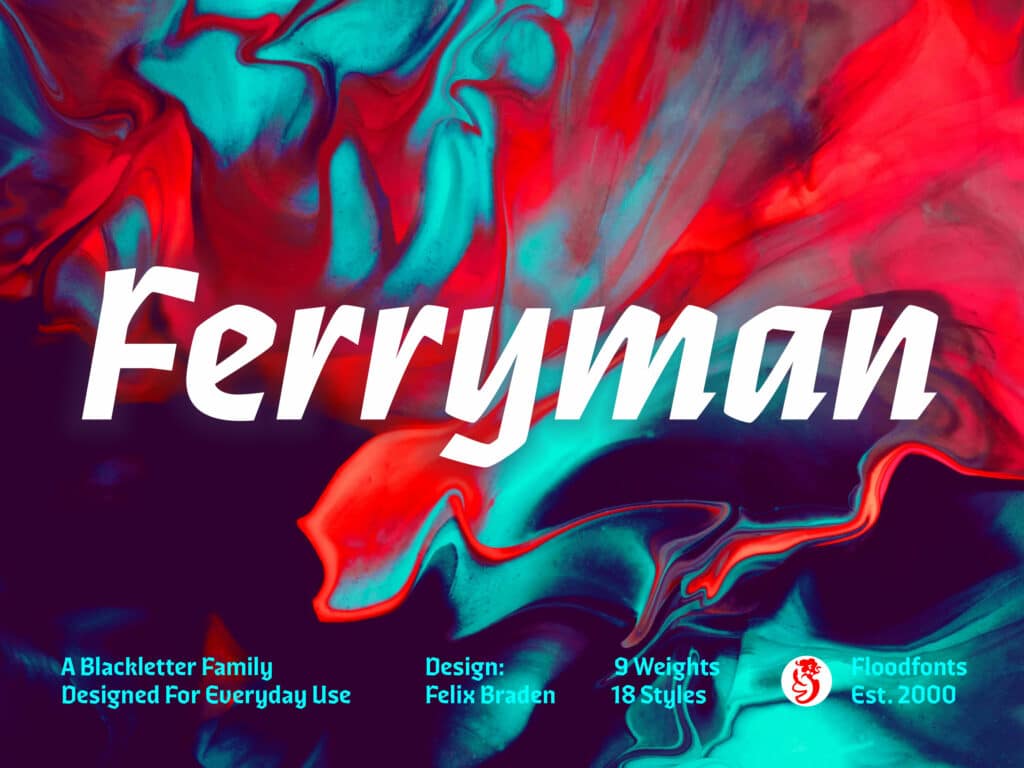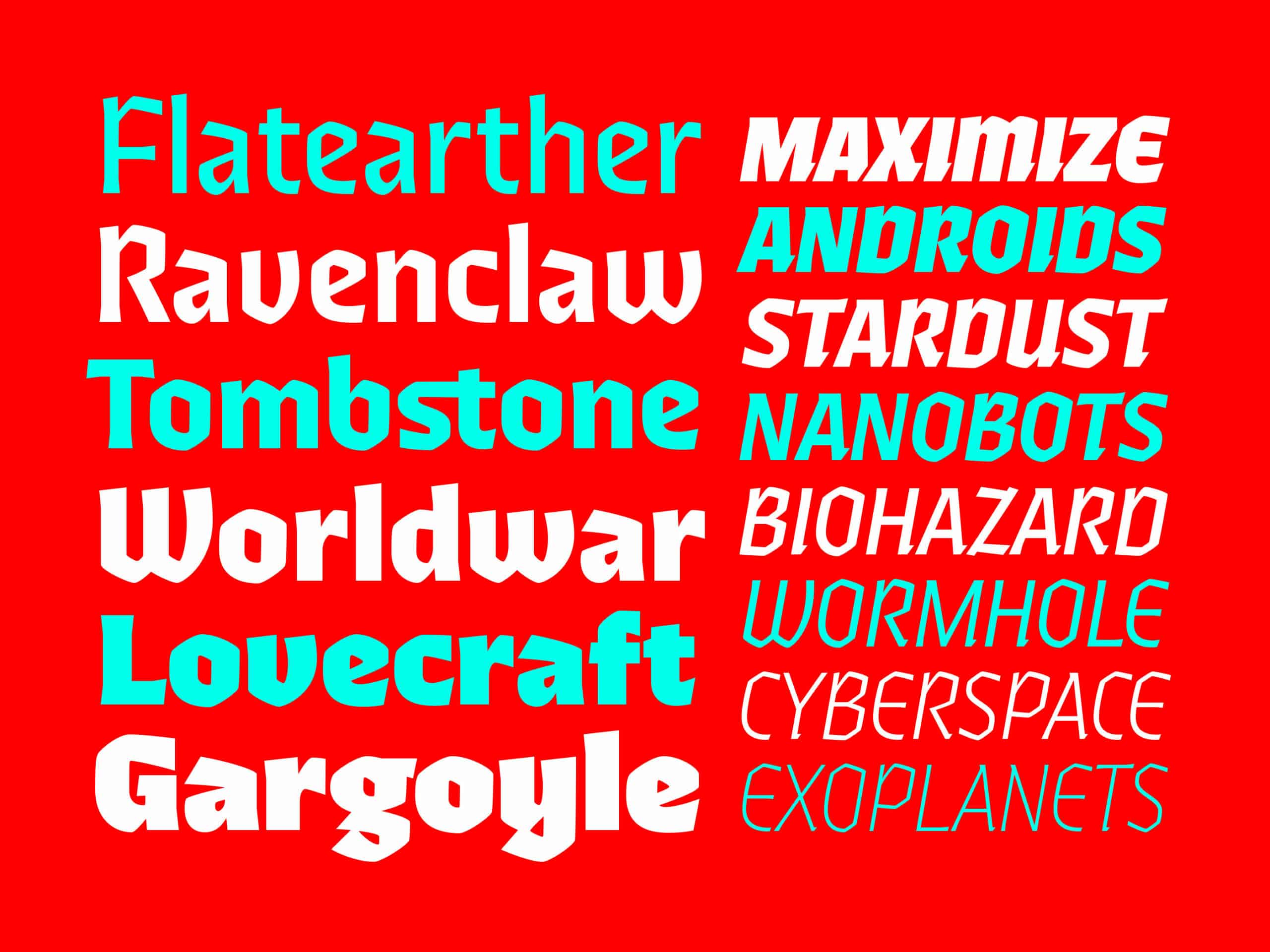
Ferryman ist eine gebrochene Schrift für ein zeitgenössisches Publikum. Ungewöhnliche Zeichen wurden durch angepasste Antiqua-Buchstaben oder durch Zeichen aus anderen historischen Schriften ersetzt, die für zeitgenössische NutzerInnen besser lesbar sind.
Ferryman ist der Gegenentwurf zu den überstrapazierten geometrischen Serifenlosen und Neogrotesken. Als ausdrucksstarke Display-Schrift mit starkem Charakter eignet sie sich perfekt für Counterculture-Projekte und progressive Konzepte, z. B. für Kunst und Design, Indie-Musik und alternative Lebensstile.
Mit neun Schnitten und passenden Kursiven bietet Ferryman eine breite Palette an kreativen Möglichkeiten. Jeder Schnitt hat 590 Glyphen, die alle west-, ost- und mitteleuropäischen Sprachen unterstützen, und wird mit vier Zahlensätzen und verschiedenen Währungssymbolen geliefert.
Über den Designprozess
„Gebrochene Schrift“ steht für ein Gestaltungsprinzip, das eine Reihe von Schriftstilen wie Textura, Fraktur oder Schwabacher umfasst, und ist keine einzelne Schriftart oder ein Schriftsystem. Obwohl diese Schriften auf den ersten Blick ähnlich erscheinen, unterscheiden sich ihre Formen erheblich – viel mehr als die der heute gängigen Antiquaschriften. Das Hauptziel bei der Gestaltung der Ferryman bestand nicht darin, eine historisch korrekte Gebrochene Schrift zu entwickeln, sondern Buchstaben zu entwerfen, die für heutige NutzerInnen gut lesbar sind und als zusammenhängende Familie funktionieren. Um dies zu erreichen, wurde nach lesefreundlichen Formen historischer Schriften gesucht und diese mit Antiqua-Elementen kombiniert. Ferryman bietet außerdem eine Vielzahl von Alternativbuchstaben, um die Benutzerfreundlichkeit zu maximieren. Dadurch haben DesignerInnen die Wahl zwischen optimaler Lesbarkeit und dem Reichtum historischer Formen.
Ferryman ist ein seltenes Beispiel für eine gebrochene Schrift mit einer Kursiven. Wie der Name schon sagt zeichnen sich gebrochene Schriften durch eine unterbrochene Linienführung aus, während kursive Schriften auf einem kontinuierlichen, geschriebenen Duktus basieren. Dies erschwert die Übertragung des Gestaltungsprinzips der Gebrochenen Schrift auf eine Kursive erheblich. Dennoch wurden bei der Recherche historische Kursivschriften entdeckt, die gut mit dem Wesen der Gebrochenen Schriften harmonieren. Diese Inspirationen stammen hauptsächlich aus kalligrafischen Ansätzen und Handletterings, konnten mit der Ferryman aber zu einer funktionierenden kursiven Satzschrift adaptiert werden.